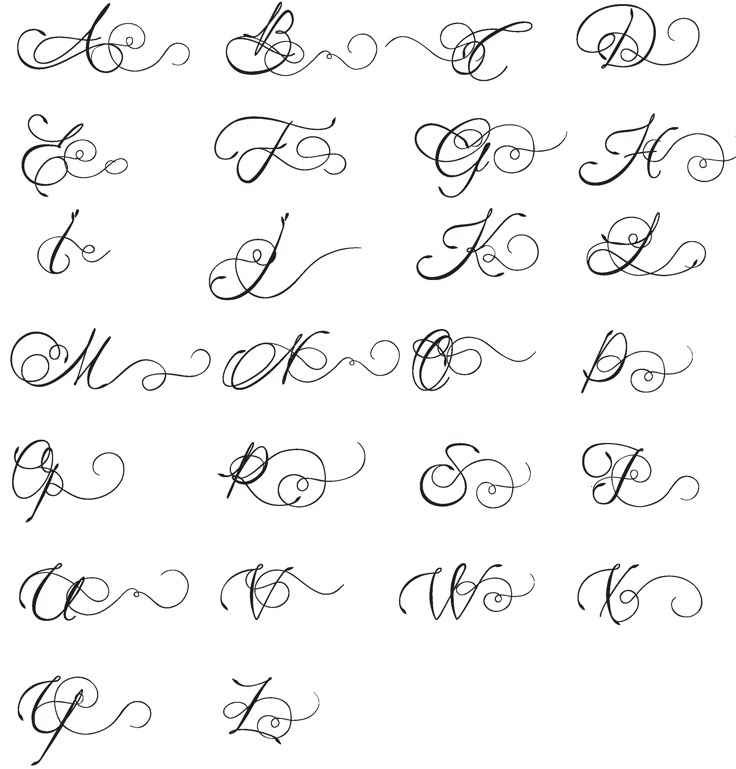
Красивый шрифт для: Bold Script – красивый шрифт онлайн
- COVES
- FELA
- SANT’ELIA
- ROBOTO
- PEACE
Большинство вариантов в этом списке бесплатны, но все же лучше перестраховаться и ознакомиться с условиями их использования.
Palatino изначально разрабатывался как экранный шрифт — для Например, для использования в надписях на вывесках. Тем не менее, это обычно используется для установки основного текста.
Книжник
ABCDE abcde 012345 &*!,.
Книжник, также известный как Книжник в старом стиле.
Не поставляется с WinXP. Поставляется с MS Office 2000.
Гарамонд
ABCDE abcde 012345 &*!,.
Гарамонд. Существует множество вариантов этого шрифта.
Не поставляется с WinXP.
Учебник века
ABCDE abcde 012345 &*!,.